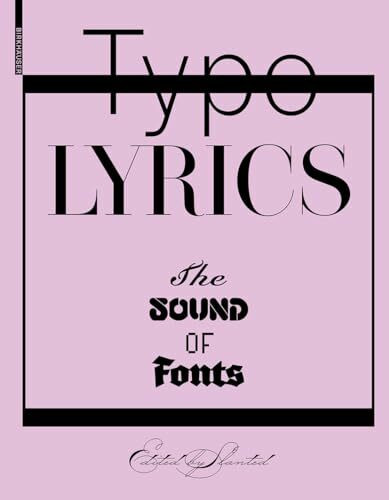
Typo Lyrics: The Sound of Fonts
"Typo Lyrics: The Sound of Fonts" von Lars Harmsen ist ein faszinierendes Buch, das die Schnittstelle zwischen Typografie und Musik erforscht. Es untersucht, wie Schriftarten und Textgestaltung die Wahrnehmung von Songtexten beeinflussen können. Harmsen präsentiert eine visuelle Reise durch verschiedene Musikgenres und zeigt, wie unterschiedliche Schrifttypen Emotionen und Stimmungen von Liedern verstärken oder verändern können. Das Buch enthält zahlreiche Beispiele und Illustrationen, die die kreative Verbindung zwischen Klang und Schriftbild verdeutlichen. Es richtet sich an Designliebhaber, Musikfans und alle, die sich für die kreative Gestaltung von Texten interessieren.